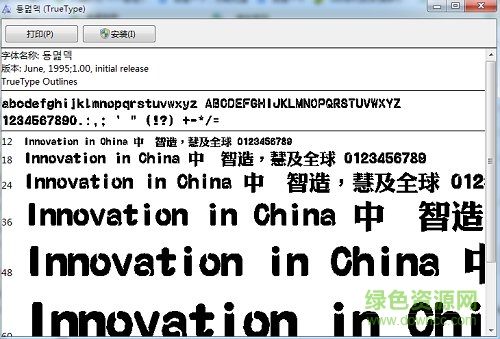
富漢通粗仿黑字體
富漢通粗仿黑字體是一款字形顯眼的粗黑體字體,這款字體筆畫又粗又黑,整體效果非常美觀,比較適用于廣告標(biāo)語、印刷等領(lǐng)域,有需要的朋友可以免費下載使用!
富漢通粗仿黑字體簡介
富漢通粗仿黑字體是一款結(jié)構(gòu)清晰的繁黑字體。該字體線條非常的粗壯,字形端正大方得體,整體效果非常的出色,且字庫完整,可以廣泛應(yīng)用于廣告設(shè)計、宣傳海報、ppt、影視制作以及任何使用文字的領(lǐng)域!